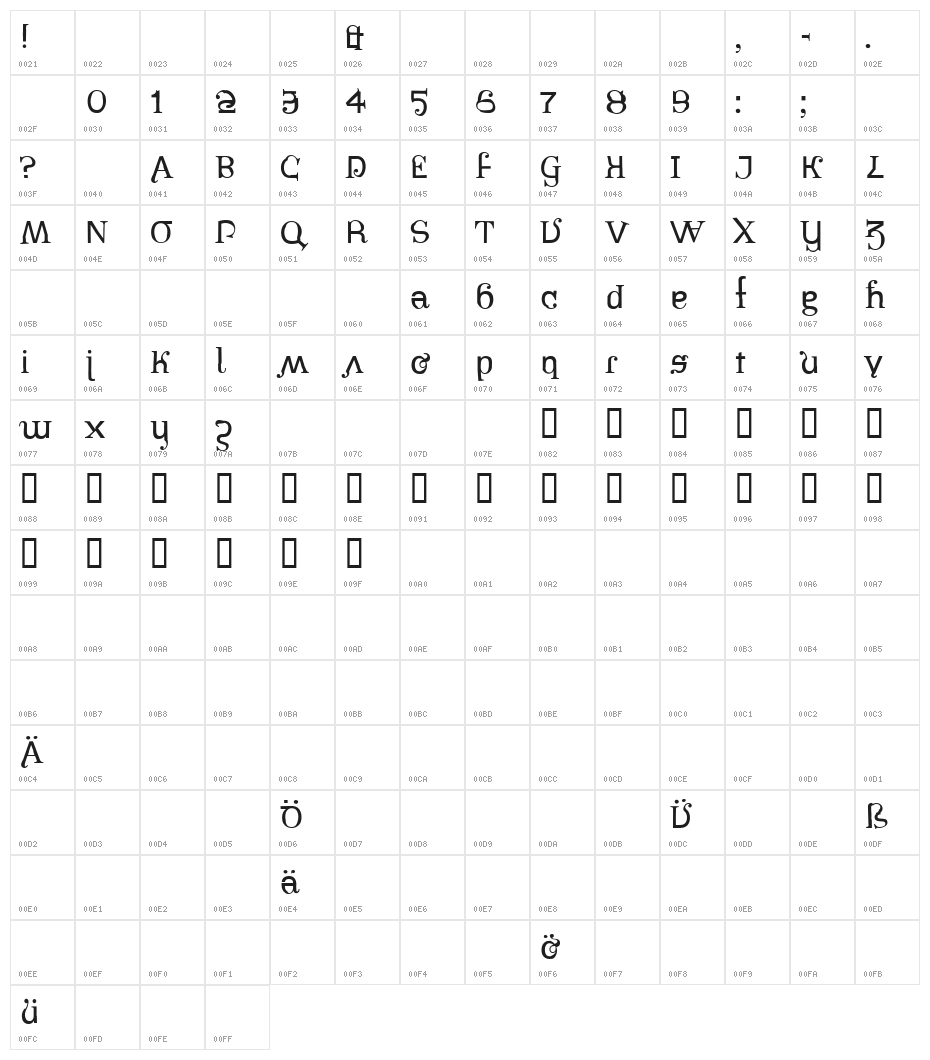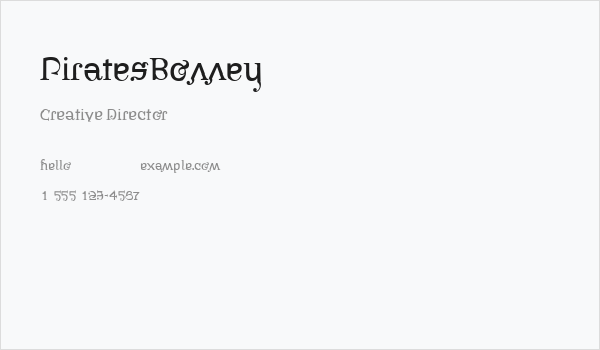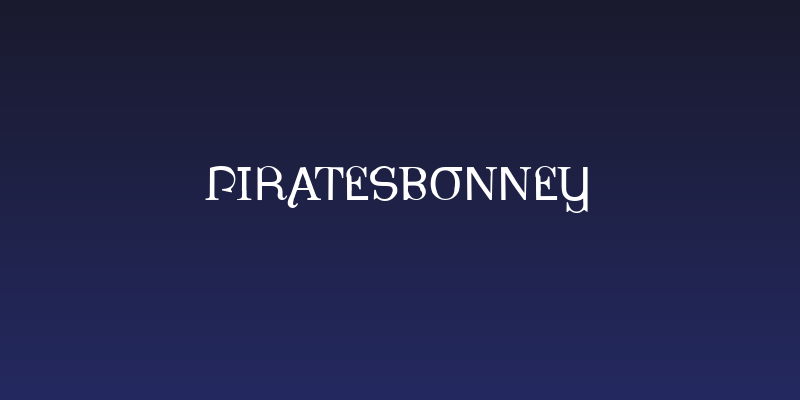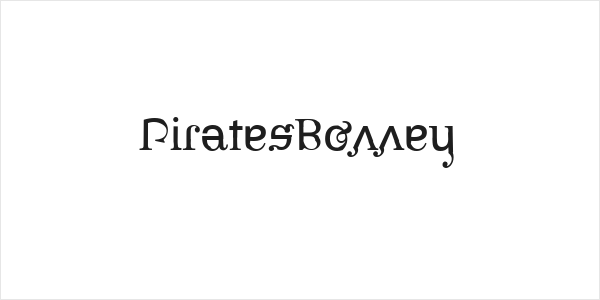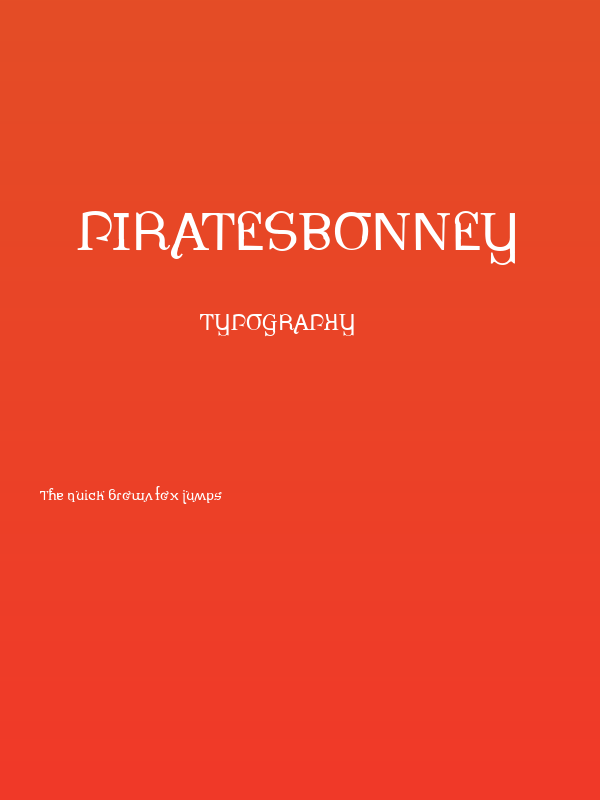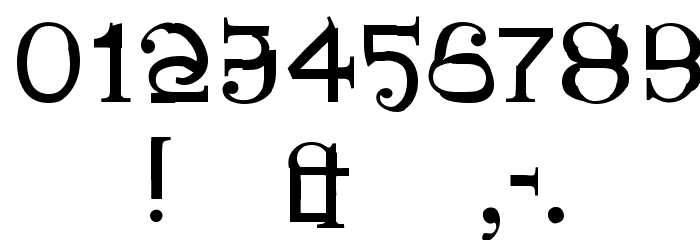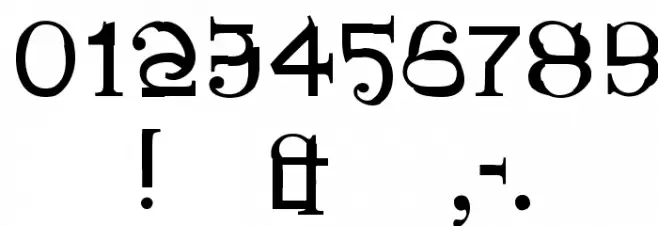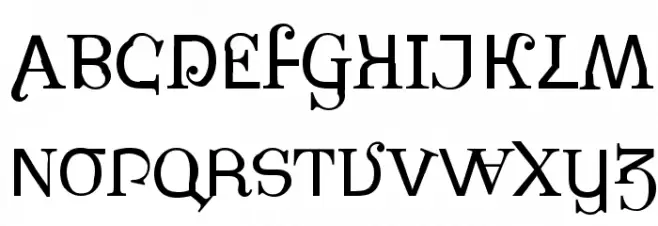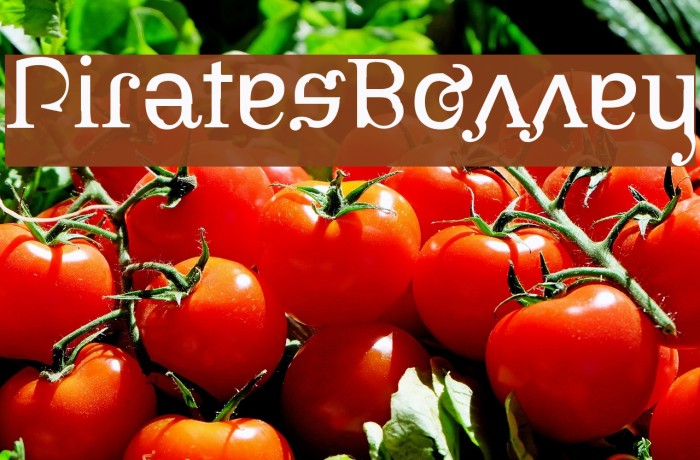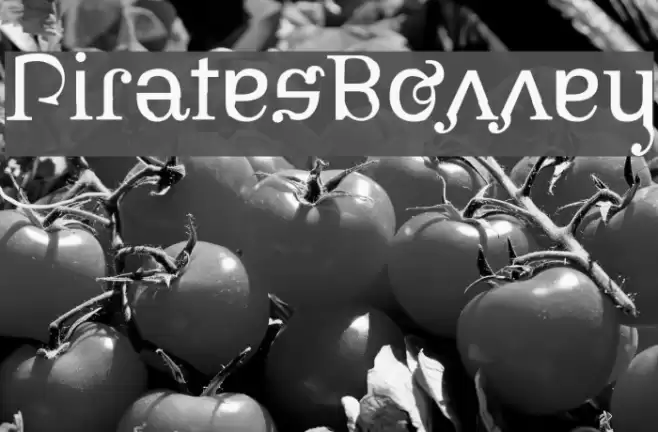
PiratesBonney Font
✎ Crazy
| Категория | Crazy |
| Область применения | Headlines, Logos, Themed Events |
| Рекомендуемые проекты | Ideal for themed events, pirate-themed parties, adventure branding, posters, and dramatic headlines. |